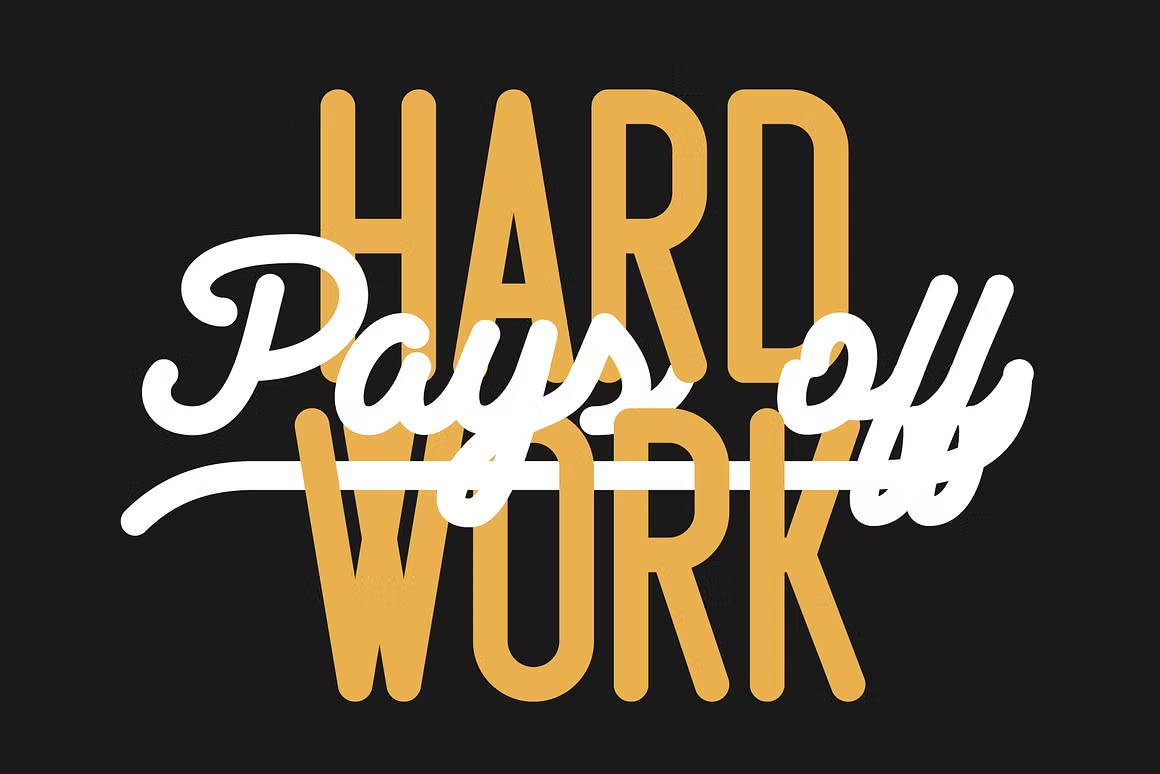
Heartland Font
Description de Heartland Font
Le trio de polices Heartland est un pack de scripts connectés audacieux et une paire arrondie sans régulière et condensée. La police est excellente pour les logos, les étiquettes de menus et de produits, les impressions, les affiches, l’image de marque et les médias sociaux.
Ce pack comprend :
Script du cœur du pays
Heartland Sans
Heartland Sans Condensé